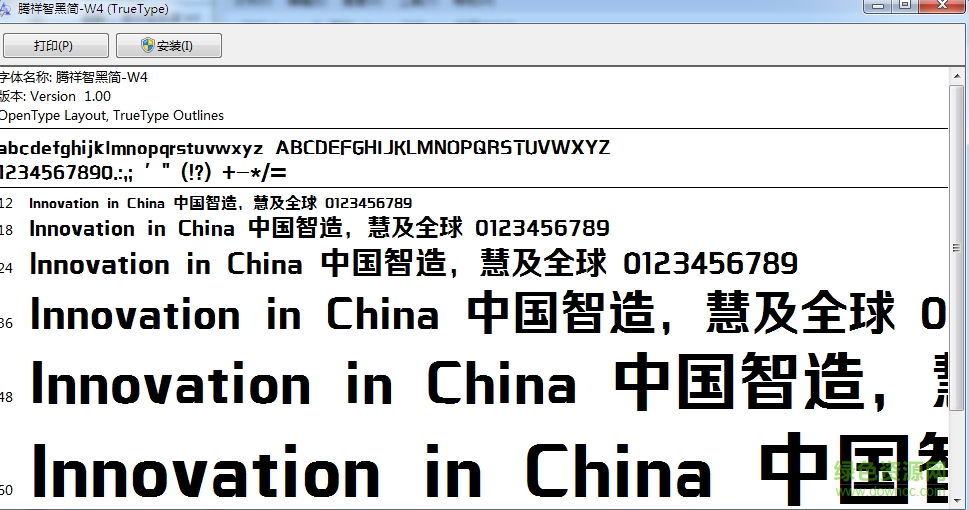
騰祥智黑簡 w4
騰祥智黑簡W4字體是一款極具設(shè)計(jì)美感的電腦黑體字體,字字精美、結(jié)構(gòu)端正、重心平穩(wěn)、美觀實(shí)用,是一款適用于正文、屏顯、標(biāo)題、設(shè)計(jì)類用字等方面的字體,喜歡就來綠色資源網(wǎng)下載!
字體簡介
騰祥智黑-W4強(qiáng)調(diào)了黑體的特征,筆畫簡潔、硬朗更穩(wěn)重大方;字形結(jié)構(gòu)方正、端莊,橫豎筆畫挺拔,軟筆畫細(xì)膩、柔美。既具有黑體的魅力又具有一定的裝飾特色,使黑體具有了靈活、生動(dòng)的特點(diǎn),從而形成自己鮮明的特色。
騰祥智黑簡W4